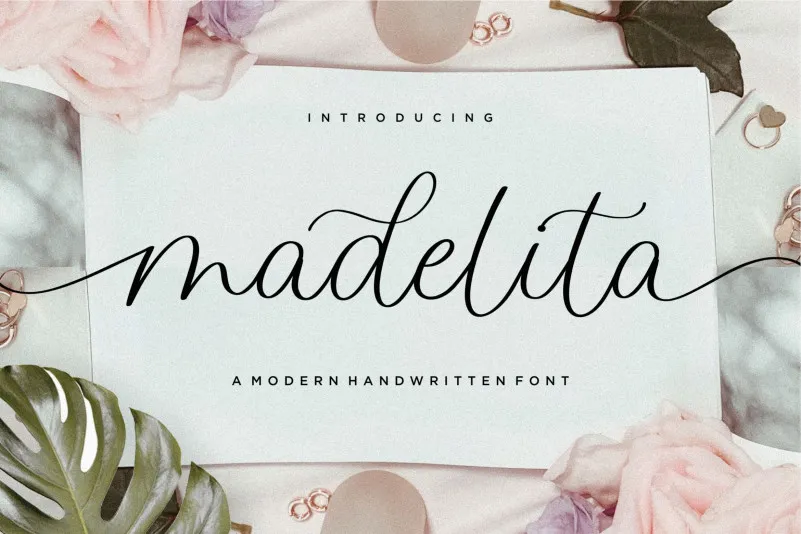
Madelita Handwritten Font – Download Grátis
Introduzimos pela Balpirick Studio a Madelita Handwritten Font, uma tipografia script elegante que transmite sofisticação e refinamento. Desenvolvida com sabedoria para complementar projetos de qualquer natureza, esta font inclui alternativas estilizadas e ligaturas personalizadas, tornando-a um match perfeito para todos os tipos de trabalhos. A Madelita Handwritten oferece uma escrita fluida e artesanal, ideal para texturas variáveis e ambientes de design requintados. Suas alternativas estilizadas permitem flexibilidade ao criar textos com nuances sutis, enquanto suas ligaturas tornam as combinações de letras mais suaves e harmoniosas. A Madelita Handwritten Font não apenas proporciona uma experiência visual agradável, mas também oferece flexibilidade ao design. Com sua elegância e sofisticação, esta font é perfeita para aplicativos como cartões personalizados, designs de site ou até mesmo editoriais de revistas, garantindo um toque refinado em qualquer projeto que ela seja usada.